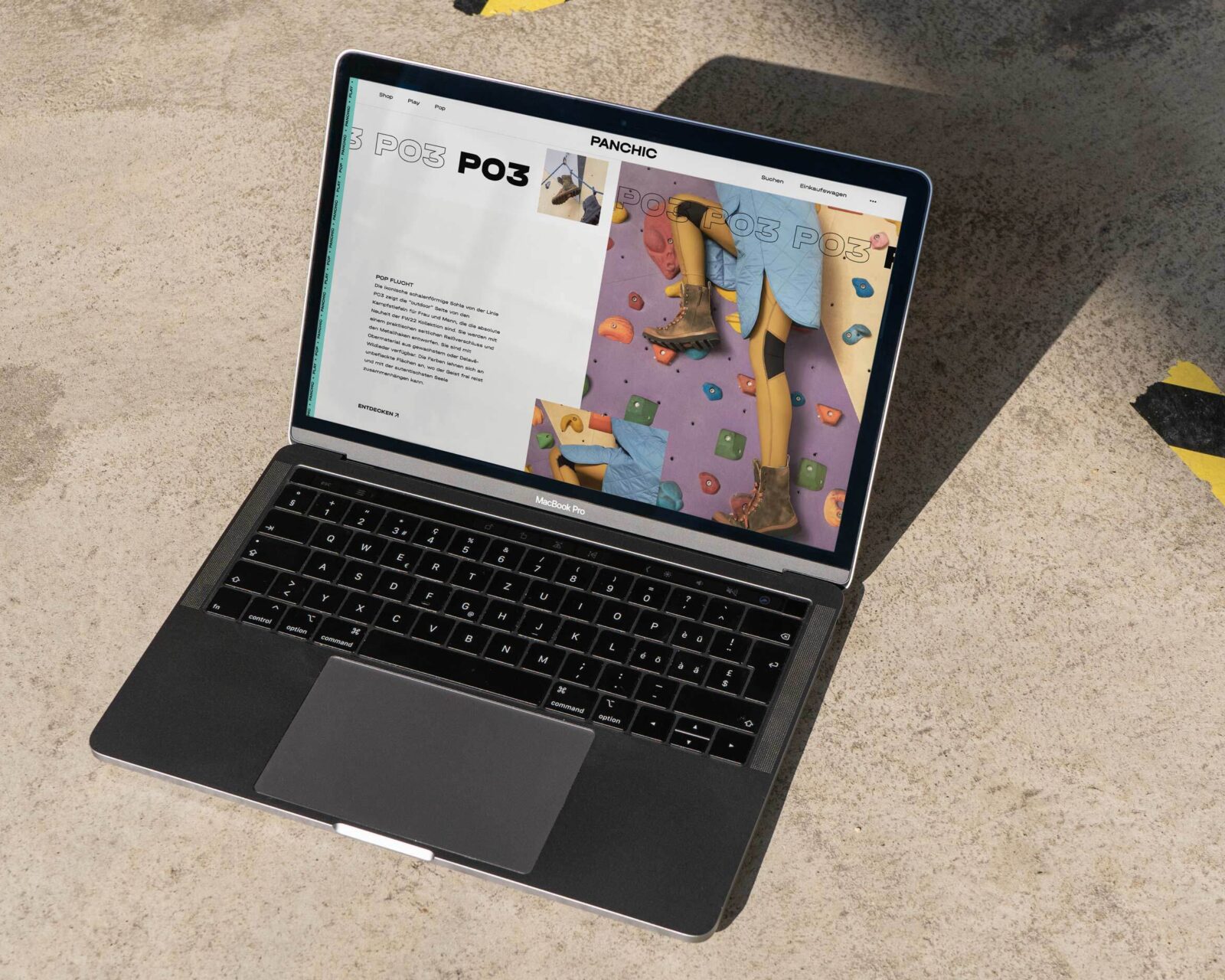
Halvar ist mit ihren industriellen Proportionen und konstruierten Formen eine pragmatische Grotesk-Schrift mit dem rohen Charme von technischen Zeichnungen. Mit 81 Stilen bietet sie ein weites Spektrum von breit- bis schmal laufend, von Hairline bis Black, von Aufrecht zu Slanted bis hin zu SuperSlanted.
In drei Subfamilien strukturiert – mit ausladender Breitschrift, wohl proportionierter Mittelschrift und kompakter Engschrift – wird Halvar zu einem Schriftsystem, das sich sowohl in der Anwendung als auch im Erscheinungsbild den Wünschen des Nutzers anpasst. Die Schrift eignet sich daher insbesondere für komplexe wie spezielle CI-Projekte. Darüber hinaus ist Halvar durch die zusätzliche Schablonenschrift auch auf den analogen Gebrauch vorbereitet.
Halvar ist nicht nur flexibel, sondern auch technisch höchst funktional. Abgesehen von der SuperSlanted, verändert sich die Breite der Wörter dank Duplex-Funktion nie – egal, ob als Light oder Bold, Aufrechte oder Slanted. So ist ein schnelles Wechseln der Schnitte möglich, ohne dass das Layout beeinflusst wird. Ideal für die effiziente Arbeit in Geschäftsberichten, Interface-Designs und immer dann, wenn der Platz knapp bemessen ist und die Anforderungen von Zeilenumbrüchen und Animationen berücksichtigt werden müssen.
Mit ihrem umfangreichen Zeichensatz unterstützt Halvar mit dem lateinischen, griechischen und kyrillischen Alphabet rund 190 Sprachen – perfekt für globales Branding, das sich über Ländergrenzen hinweg behauptet. Um einen hohen Standard in allen Glyphen zu gewährleisten, wurden sowohl die griechischen als auch die kyrillischen Schriftzeichen in Absprache mit Muttersprachler:innen entwickelt.
Darüber hinaus enthält das umfangreiche Schriftsystem der Halvar neben Tabellenziffern selbstverständlich auch hochgestellte wie Bruchziffern und lokale Alternativen. Halvar ist eine echte Anpassungskünstlerin: Durch den Einsatz von alternativen Zeichen kann zwischen zwei Schriftstilen gewechselt werden. So besteht die Möglichkeit neben dem normalen Schriftbild auch noch zwischen einem schlichten und einem für die Lesbarkeit in kleinen Texten und Interface-Designs optimierten Zeichen zu wählen.
Mit manuellem TrueType-Hinting und dem besonderen Augenmerk auf textrelevante Schnitte, einer großen x-Höhe, zeitgemäßen Proportionen und einem robusten Design ist Halvar für die Bildschirmdarstellung optimiert und für typografische Herausforderung von Benutzeroberflächen gerüstet.
Die komplexe Schriftfamilie, die mehrdimensional gedacht und entwickelt wurde, kann unkompliziert durch individuelle Stile ergänzt werden: Sollten andere Breiten oder Italics mit anderen Winkeln benötigt werden, steht der Variable Font bereit.
- Modern Cyrillic Award 2021
- Im Wettbewerb Modern Cyrillic 2021 als gelungenes Beispiel für den aktuellen Stand der kyrillischen Schriftentwicklung ausgezeichnet.
- 27 Stile aus 9 Gewichten in Normal und 2 Slanted Versionen, mehr als 900 Glyphen je Schrift.